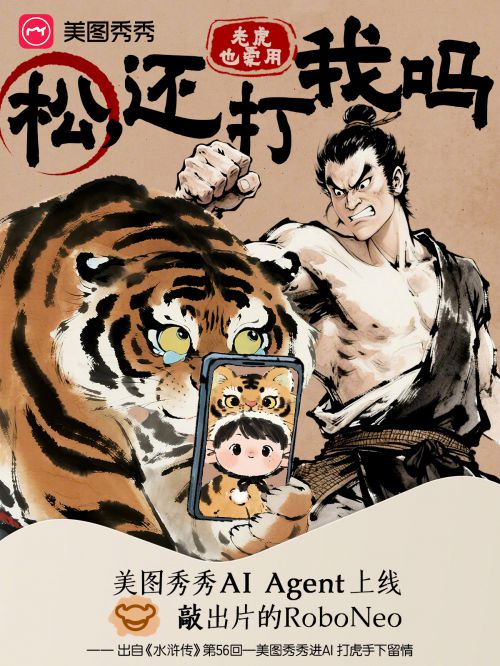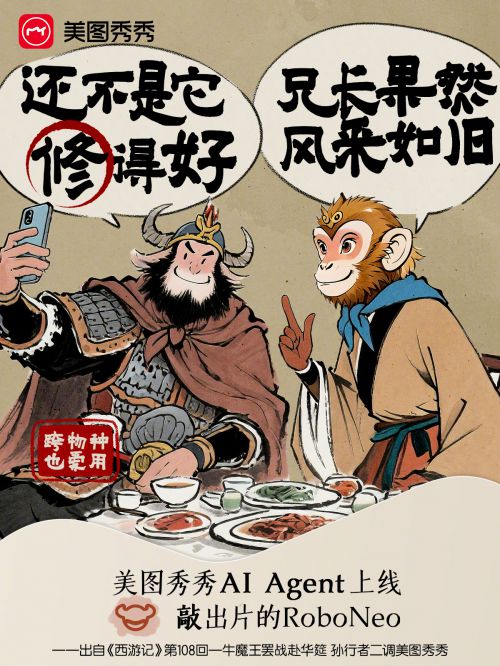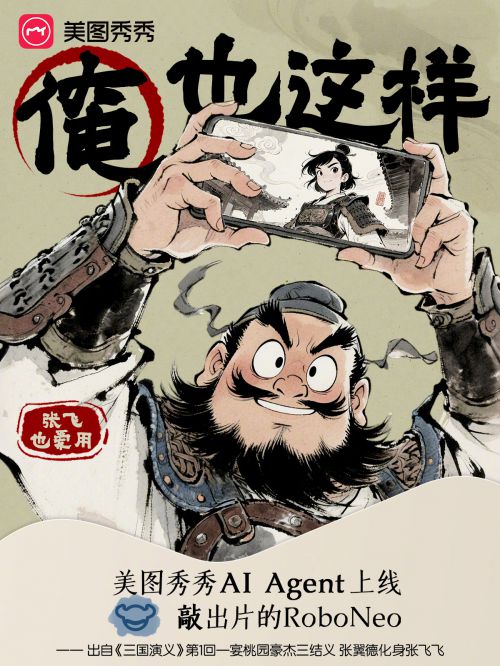
点字隶楷
点字隶楷是一款融合楷书方整结构与隶书典雅体势的书法手写体,兼具中国风的古典韵味与手写笔触的力量感,为设计注入复古雅致的视觉张力。 点字隶楷字形方正稳重,重心居中,中宫适中,既延续楷书端庄规整的布局逻辑,又融入隶书横势开张的舒展气度,收放关系清晰,展现“刚柔并济”的结构美学。笔型设计巧妙糅合双体精髓——楷书方头起笔的硬朗与隶书波磔的灵动并存,横画保留汉隶经典垂头起笔,撇捺小笔画增添弹性弧度,装饰元素细腻却不繁复,让每一笔都兼具力量感与韵律美。 笔画粗细均匀适中,连接多为断开,保留手写书法的自然呼吸感,整体呈现“古而弥新”的独特气质。作为点字库会员商用字体,点字隶楷适用于国潮文创、传统品牌标识、书法主题海报等场景,让古典书法美学与现代设计需求无缝衔接,传递深厚文化底蕴与鲜活设计魅力。